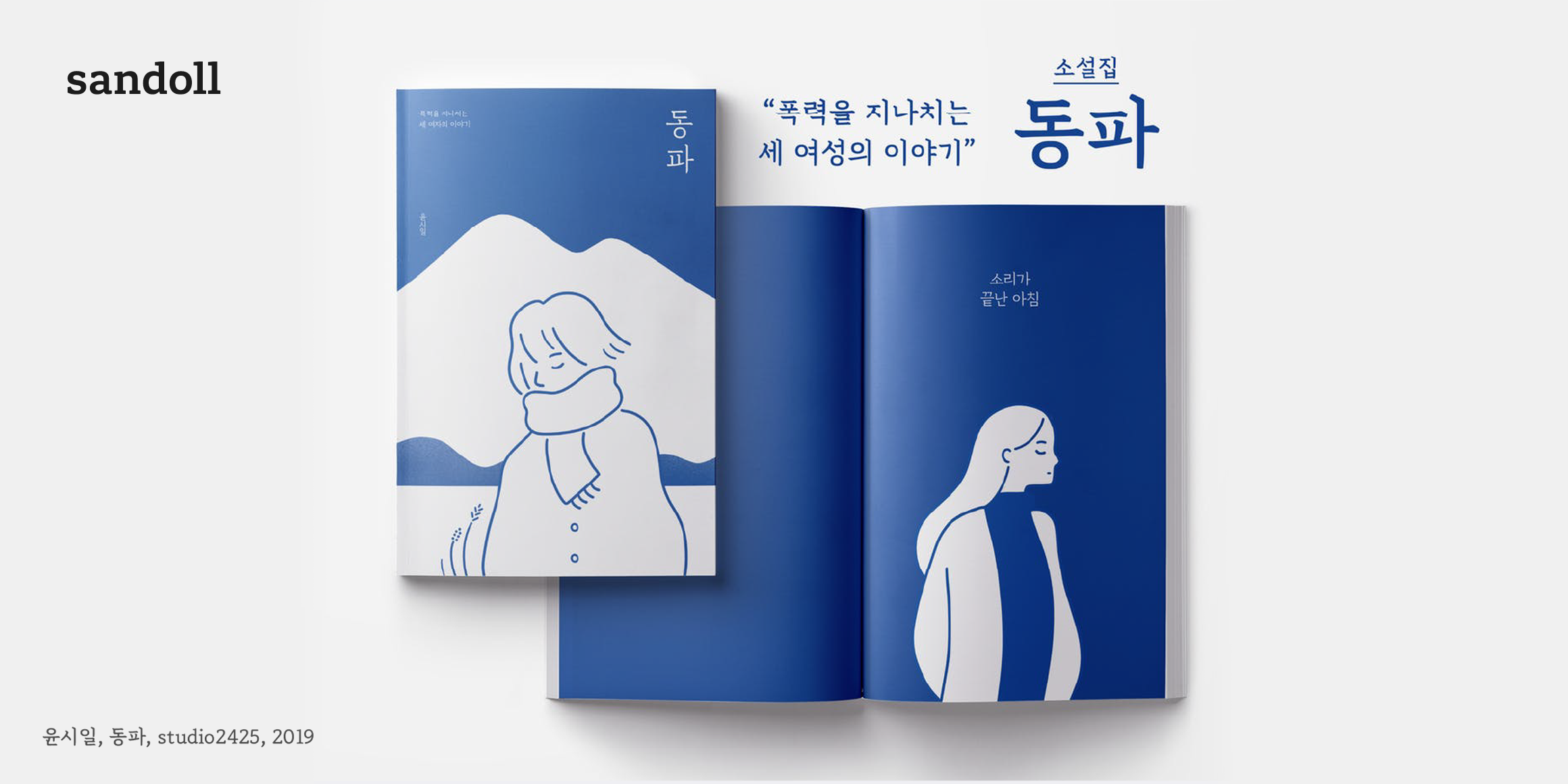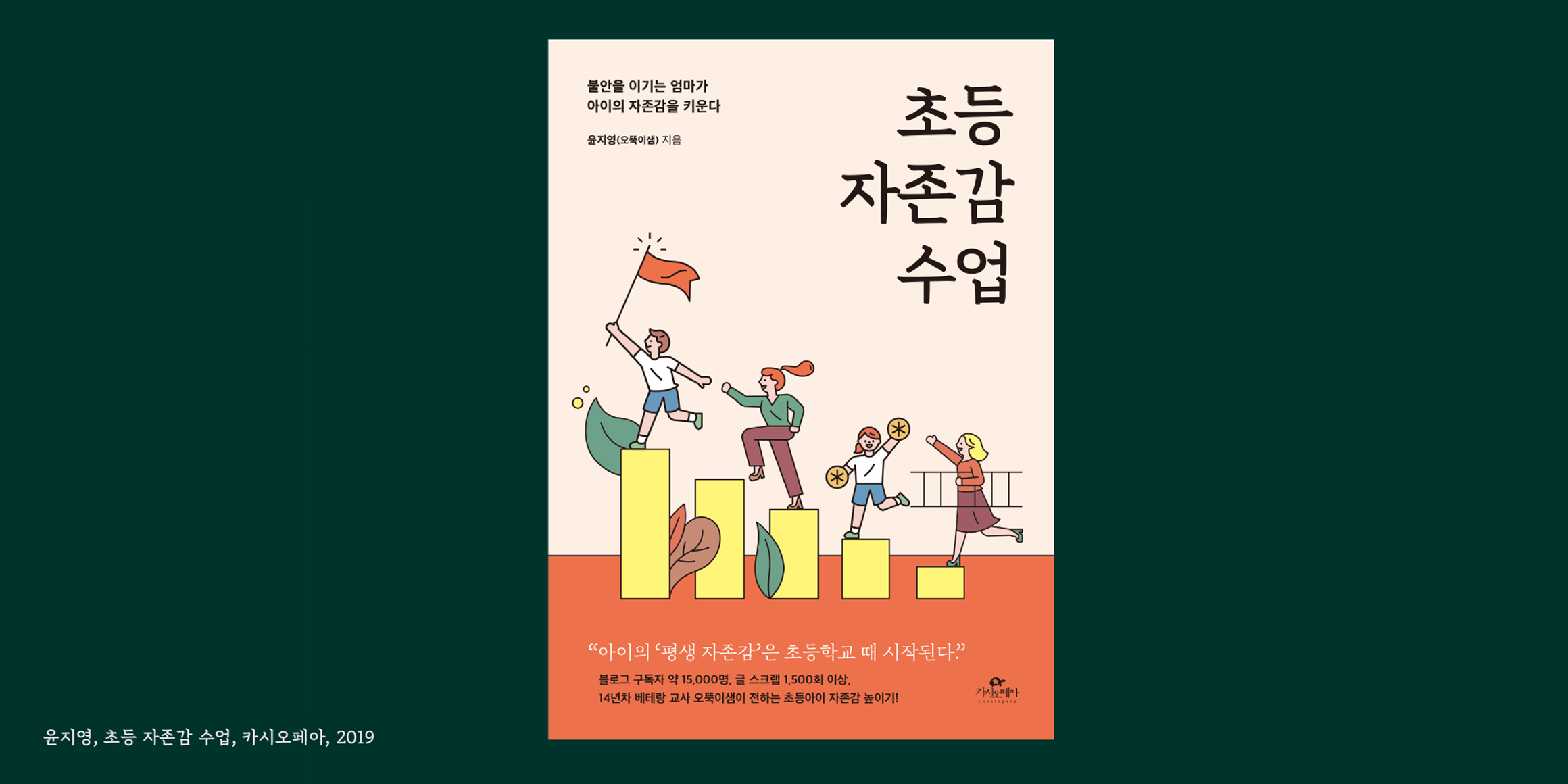
Sandoll 눈솔
분류 Serif,부리
종수 3종
산돌 눈솔은 단단하고 직선적인 인상을 지닌 부리계열 폰트다.
기존의 부리계열 폰트가 미려하고 곡선적인 인상을 갖고 있었다면 산돌 눈솔은 곧은 형태, 완만한 기울기, 넓은 받침 같은 구조들을 활용해 안정적이고 견고한 느낌을 준다.
제목과 본문에 모두 사용하기 편리하며, 조판했을 경우에도 부담스럽지 않고 편안하게 읽히는 장점을 지녔다.
산돌의 폰트 중 Adobe-KR-9 규격이 첫 번째로 적용되어 기존에 표현하지 못했던 뷁, 똠얌꿍 같은 표현들이 가능해졌다.
또한 기존의 Bold에 이어 Thin, Regular가 새롭게 추가되어 사용성이 확장되었다.
• 김진희 김슬기 박진현
• Sandoll 눈솔 / Sandoll Nunsol